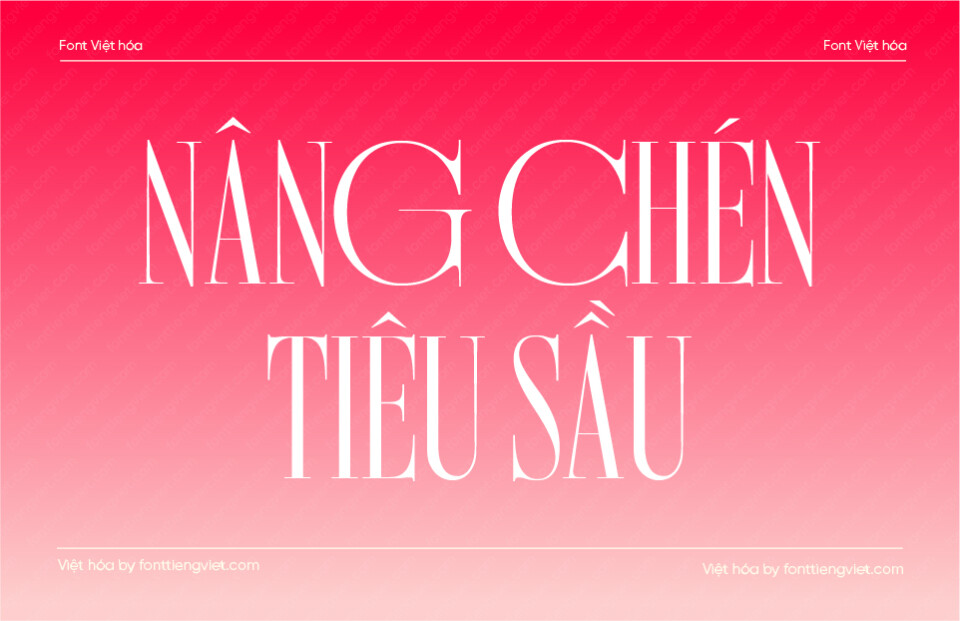
Font Việt hóa 1FTV VIP Chloris SemiCondensed
Font Việt hóa 1FTV VIP Chloris SemiCondensed – Sự kết hợp hoàn hảo giữa nét hiện đại và tinh tế
Giới thiệu về Font Việt hóa 1FTV VIP Chloris SemiCondensed
Trong thế giới thiết kế đồ họa ngày nay, việc lựa chọn một Font Miễn Phí chất lượng không chỉ giúp thông điệp truyền tải rõ ràng mà còn tạo nên dấu ấn riêng biệt cho tác giả. Font Việt hóa 1FTV VIP Chloris SemiCondensed là một ví dụ điển hình cho sự giao thoa giữa vẻ đẹp cổ điển và hơi thở hiện đại. Đây là phiên bản được tối ưu hóa đặc biệt dành riêng cho người dùng Việt Nam, giải quyết hoàn toàn vấn đề lỗi dấu và khoảng cách chữ thường gặp ở các bộ font ngoại nhập. Với thiết kế dạng SemiCondensed (hẹp vừa phải), bộ chữ này giúp tiết kiệm không gian dàn trang nhưng vẫn giữ được độ thoáng đạt, dễ đọc cho người xem ở mọi lứa tuổi.
Đặc điểm nổi bật của bộ Font Việt hóa 1FTV VIP Chloris SemiCondensed
Thiết kế thanh lịch và cấu trúc chữ khoa học
Điểm thu hút đầu tiên của Font Việt hóa 1FTV VIP Chloris SemiCondensed chính là hệ thống các nét chữ được trau chuốt tỉ mỉ. Các đường nét không quá mảnh khảnh nhưng cũng không quá dày đặc, tạo nên một sự cân bằng thị giác tuyệt vời. Kiểu dáng SemiCondensed giúp các con chữ trông cao ráo hơn, mang lại cảm giác chuyên nghiệp và sang trọng cho các ấn phẩm thiết kế. Đặc biệt, bộ font này cực kỳ phù hợp cho các bạn học sinh dùng để làm slide thuyết trình hoặc trang trí báo tường điện tử nhờ sự gọn gàng và trang nhã của nó.
Khả năng hiển thị đa dụng trên nhiều nền tảng
Dù bạn đang sử dụng các phần mềm thiết kế chuyên nghiệp như Adobe Photoshop, Illustrator hay các ứng dụng văn phòng quen thuộc như Word, PowerPoint, Font Việt hóa 1FTV VIP Chloris SemiCondensed đều vận hành mượt mà. Hệ thống dấu tiếng Việt được đội ngũ 1FTV chăm chút kỹ lưỡng, đảm bảo các dấu thanh như huyền, sắc, hỏi, ngã, nặng được đặt đúng vị trí, không bị đè lên chữ hay làm méo mó bố cục chung. Điều này giúp người dùng tiết kiệm rất nhiều thời gian trong khâu hậu kỳ và chỉnh sửa văn bản.
Ứng dụng thực tế của Font Việt hóa 1FTV VIP Chloris SemiCondensed trong đời sống
Sáng tạo nội dung giáo dục và học tập
Tại các nhà trường, việc truyền đạt kiến thức thông qua hình ảnh trực quan là vô cùng quan trọng. Sử dụng Font Việt hóa 1FTV VIP Chloris SemiCondensed giúp các thầy cô giáo tạo ra những bộ giáo án điện tử sinh động hơn. Sự rõ ràng của phông chữ này hỗ trợ học sinh dễ dàng theo dõi bài giảng từ xa mà không gây mỏi mắt. Ngoài ra, các bạn sinh viên cũng có thể dùng nó để thiết kế bìa tiểu luận hoặc CV xin việc nhằm tạo ấn tượng mạnh mẽ với nhà tuyển dụng ngay từ cái nhìn đầu tiên nhờ phong cách tối giản mà đẳng cấp.
Trang trí và thiết kế thương hiệu cá nhân
Nếu bạn đang ấp ủ dự án kinh doanh nhỏ hoặc muốn làm mới trang mạng xã hội của mình, bộ font này là một lựa chọn không thể bỏ qua. Nó rất thích hợp để làm tiêu đề cho các bài đăng Facebook, Instagram hay thiết kế logo đơn giản. Font Việt hóa 1FTV VIP Chloris SemiCondensed mang lại cảm giác tin cậy và hiện đại, giúp thông điệp của bạn tiếp cận người xem một cách tự nhiên và đầy cảm xúc.
Kết luận về giá trị của phông chữ Việt hóa
Việc sử dụng Font Việt hóa 1FTV VIP Chloris SemiCondensed không chỉ nâng cao thẩm mỹ cho tác phẩm mà còn thể hiện sự trân trọng đối với ngôn ngữ dân tộc. Qua việc tối ưu hóa cho tiếng Việt, bộ font này đã xóa bỏ rào cản kỹ thuật cho các nhà thiết kế không chuyên. Hãy cùng trải nghiệm sự khác biệt ngay hôm nay và đừng quên truy cập Font Miễn Phí, Font Việt Hóa, Font Việt hóa 1FTV VIP Chloris SemiCondensed để tải về những tài nguyên sáng tạo tốt nhất cho hành trình học tập và làm việc của bạn. Sự sáng tạo là không giới hạn khi bạn có trong tay những công cụ hỗ trợ đắc lực và chuẩn xác nhất.